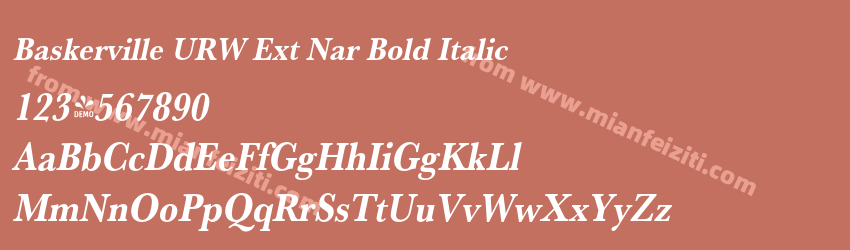
Baskerville URW Ext Nar Bold Italic
字体名称: Baskerville URW Ext Nar Bold Italic
本款“Baskerville URW Ext Nar Bold Italic”是一款书写很新颖的字体,字体大方,适合各种设计作品使用!欢迎下载!